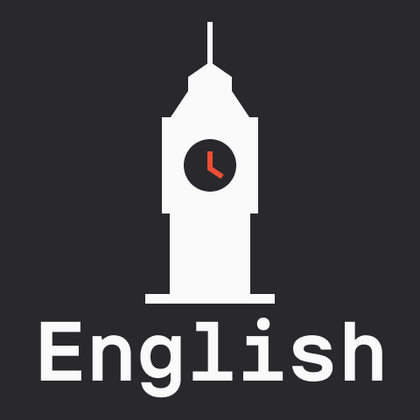
Подборка Английских шрифтов
Шрифты с поддержкой английского языка — база для любых международных проектов. В таких коллекциях, как у TypeType, английские шрифты гарантированно включают все необходимые символы: от стандартных букв до специальных знаков препинания. Это важно для дизайна сайтов, презентаций или упаковки — текст будет отображаться корректно в любой англоязычной стране. Подобные гарнитуры экономят время, исключая ошибки вёрстки и проблемы с совместимостью.
Выберите подходящий шрифт с поддержкой Английского языка. Огромная коллекция шрифтовых семейств для любых целей и задач: набор больших текстовых массивов, оформление заголовков для веб-сайтов и печатных изданий, печать на текстиле и других материалах, оформление вывесок и афиш.
Каждый из представленных шрифтов содержит Английский алфавит. Широкий выбор символов, знаков валют и пунктуации, шрифтовых начертаний и OpenType фич позволят применять один шрифт для разных проектов. Знаки расширенной латиницы, содержащие диакритические знаки, расширят возможности использования шрифта для разных стран.
Каждый шрифт безупречен с технической точки зрения. Многие шрифты из коллекции содержат вариативное начертание, с помощью которого можно создавать уникальное начертание для проекта.
TT Nooks является экспериментальным шрифтовым семейством состоящим из высококонтрастной антиквы TT Nooks и прямого курсива TT Nooks Script. Если бы TT Nooks была человеком (живой), то её можно было описать как элегантную даму с независимым и твёрдым характером.
TT Severs — это геометрический гротеск с ярко выраженными элементами внутренних скруглений. Отличительной особенностью TT Severs является необычная форма внутренних овалов, которая отсылает нас к стилю традиционной арабской письменности.